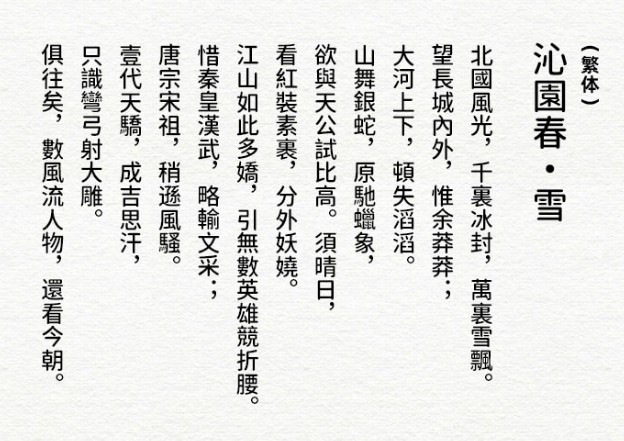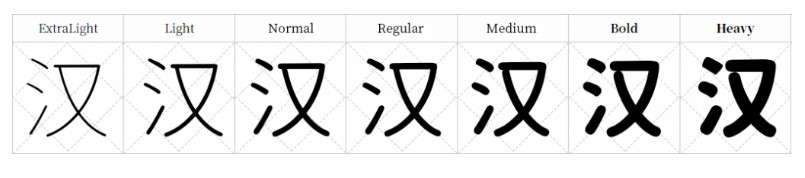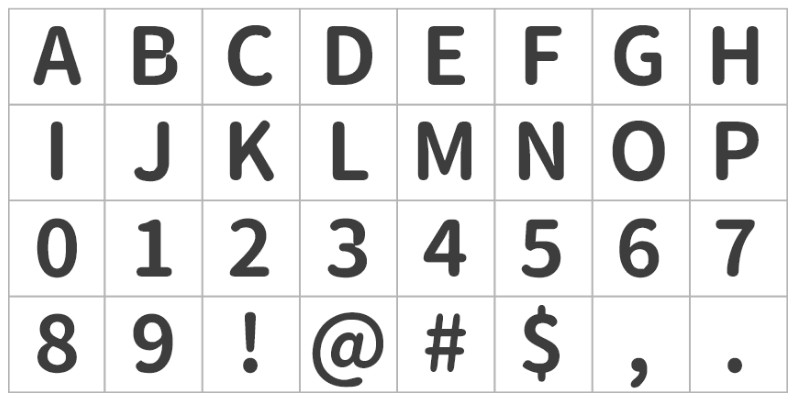
资源圆体是思源黑体的直接变圆版,所以它的特徵跟源柔黑体基本上是一样的,但是资源圆体对简体支持十分好!简体不缺字!而且资源黑体和思源黑体一样,拥有7个字重(优秀),基本上满足大部分的设计需求。所以本站推荐使用这款字体替换掉你电脑上的源柔黑体吧。
与源泉圆体有何不同?
资源圆体与源泉圆体最大的区别就是字体的笔画上有所不同。资源圆体保留着字体的脚,而源泉圆体把字体上的脚都拔除了。